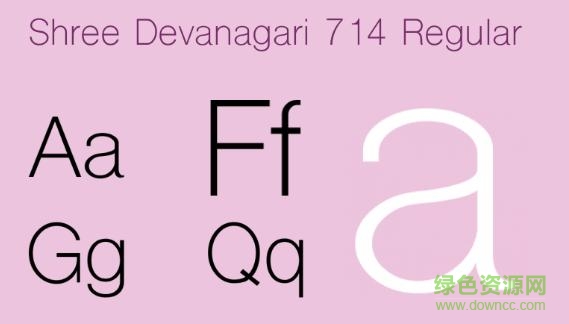
shree devanagari 714
shree devanagari 714字體是一款美觀好看的外文字體,字形規(guī)整,輪廓清晰,放大縮小不易變形,適用于各個(gè)領(lǐng)域,喜歡這款好看的字體就來(lái)綠色資源網(wǎng)下載體驗(yàn)吧!
shree devanagari 714字體